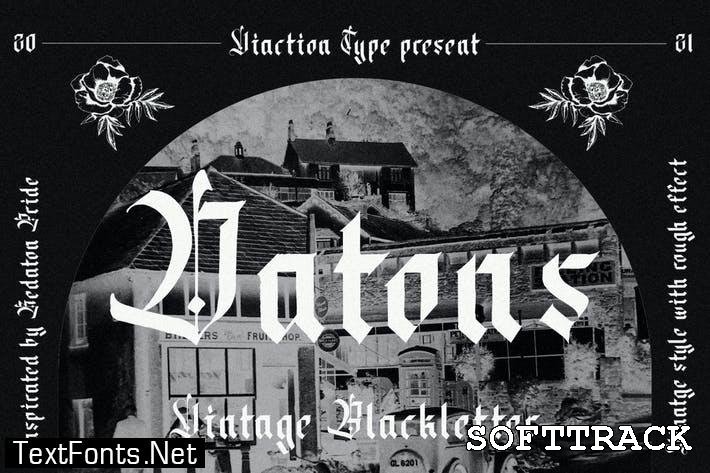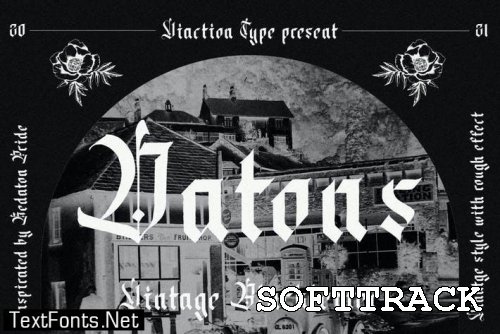
Datons - Vintage Blackletter
Datons  is een lettertype dat is gemaakt met een vintage tintje, maar de kenmerkende Blackletter-lettertypestijl niet verliest. Perfect voor krantenkoppen of merknamen of andere spookachtige en vintage designbehoeften. Deze lettertypen zijn onder meer: